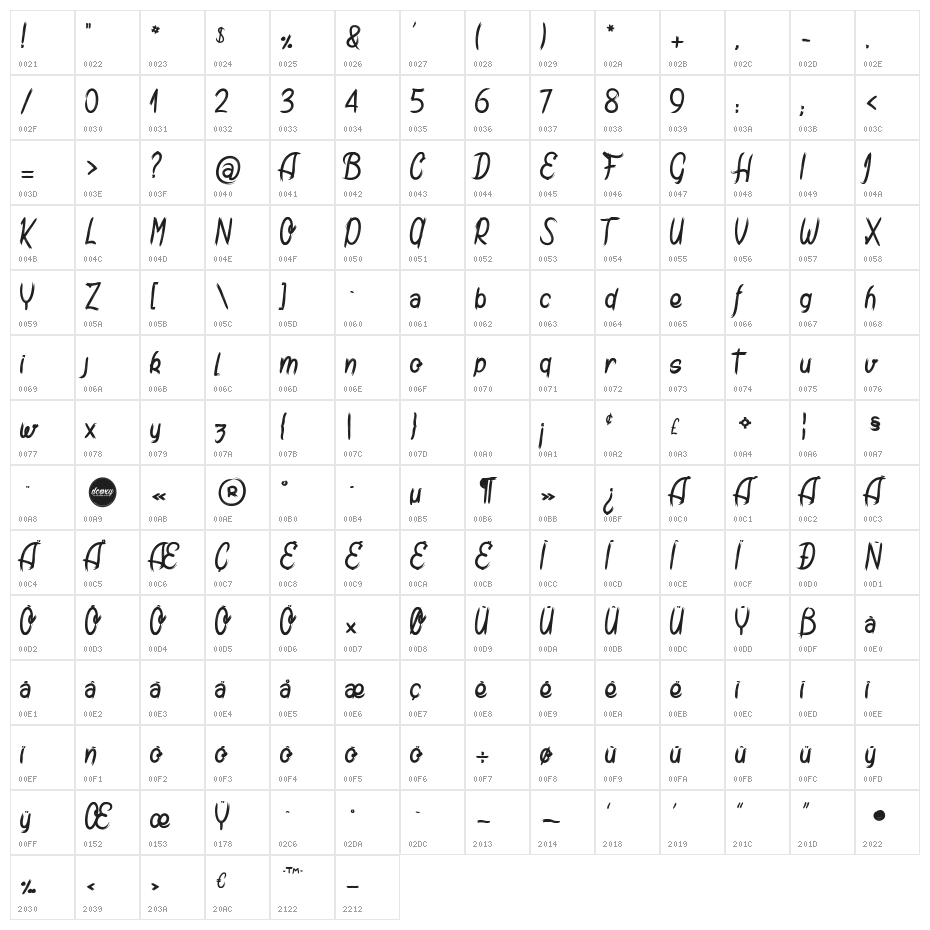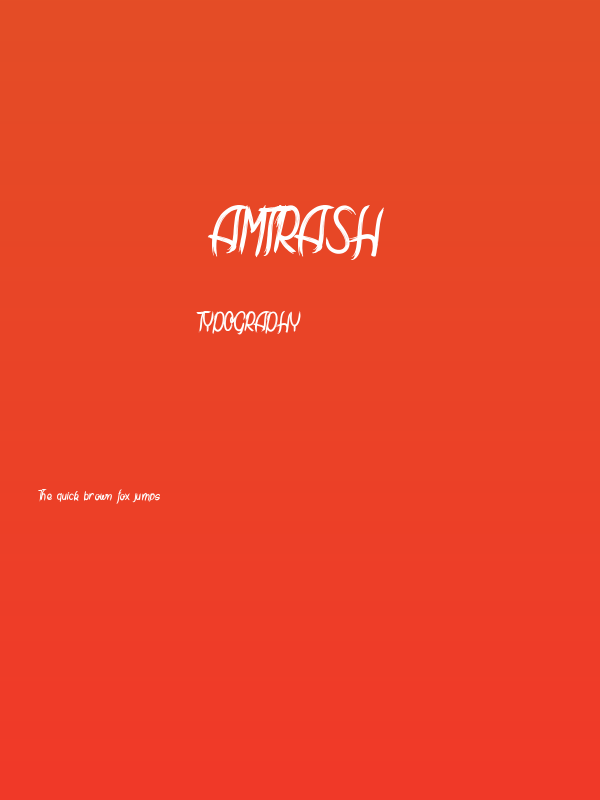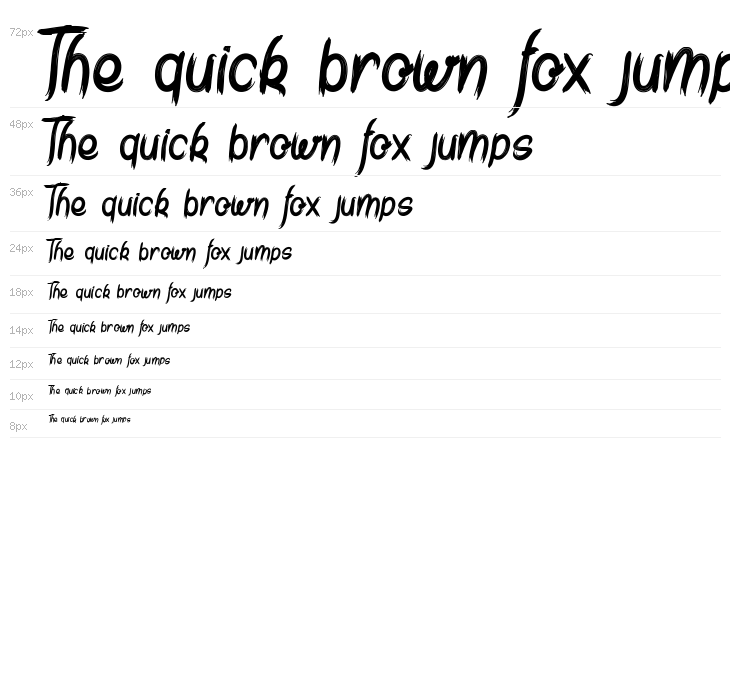
Amtrash Font
✎ Script
| 分类 | Script |
| 使用场景 | Logos, Headlines, Posters |
| 推荐项目 | Ideal for branding, posters, album covers, and any project needing a bold, artistic flair. |